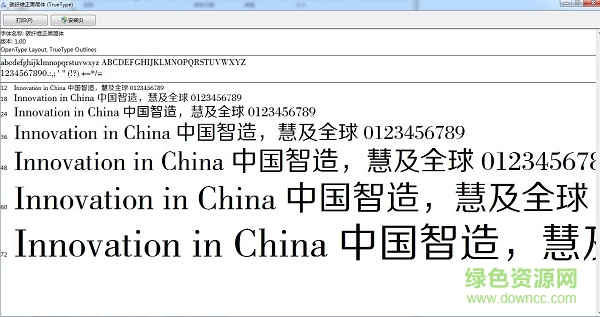
碳纖維正黑簡體
txwzhjw gb1 0是什么字體?txwzhjw gb1 0字體就是碳纖維正黑簡體,該字體保持了黑體的基本特點,筆畫棱角分明,字形挺拔端正,有需要的小伙伴快來本站免費下載吧!
中文黑體介紹
漢字的黑體是在現(xiàn)代印刷術(shù)傳入東方后依據(jù)西文無襯線體中的黑體所創(chuàng)造的。由于漢字筆劃多,小字黑體清晰度較差,所以一開始主要用于文章標題。但隨著制字技術(shù)的精進,已有許多適用于正文的黑體字型。
碳纖維正黑簡體
黑體字體特征
這個詞的范疇和無襯線字體(Sans-serif)是類似的。所以在中文字體中常用“黑體”,在西文中常用“無襯線體”的稱呼。而宋體就可以被稱作襯線字體。 “黑體”在日文中被稱為Goshikku-tai(直譯即“哥特體”)。